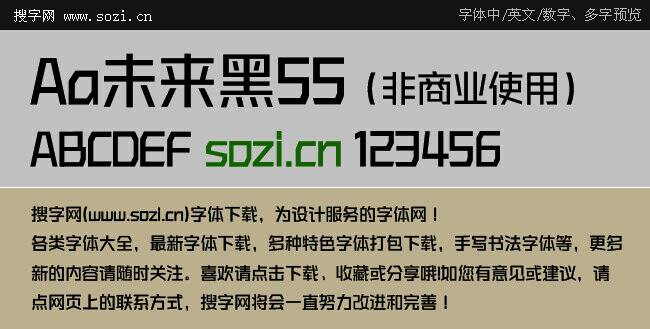
Aa未来黑55
搜字网给大家提供一款Aa未来黑55(非商业使用)中文字体下载,该字体是一款艺术黑体,字体笔画粗细一致,运笔自然流畅,结构清晰易识读,以简单斜切的笔画和方正饱满的结构,来体现机械冷静却充满力量的科技感,适合书装设计、包装、海报设计等应用(此字体为个人非商用版,商用可以联系QQ:1006760504)。